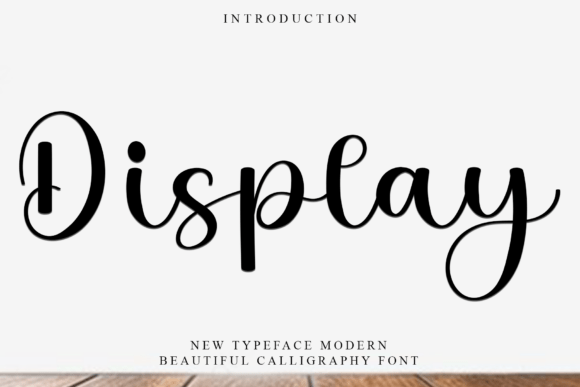
Display
Display – A Fonte Calligráfica que Transforma Seu Projeto
Se você busca uma tipografia que una elegância e versatilidade, a Display é a escolha ideal. Desenvolvida como uma fonte moderna de caligrafia, ela combina curvas suaves com traços marcantes, criando um visual refinado e ao mesmo tempo acessível. Perfeita para wedding invitations, cartões de felicitação, branding, logotipos, embalagens e design editorial, a Display garante que cada palavra pareça única e memorável.
- Ascendentes e descendentes fluídos: proporcionam um movimento gracioso que confere dinamismo ao texto.
- Contraste equilibrado entre linhas grossas e finas: aumenta a legibilidade sem perder a sofisticação.
- Charme de escrita à mão: traz um toque humano e acolhedor, ideal para projetos que precisam de personalidade.
- PUA encoded: acesso fácil a todos os glifos e ligaturas avançadas, facilitando a criação de layouts ricos.
- Versatilidade tipográfica: funciona impecavelmente em headlines impactantes ou em textos corridos fluídos.
Por que escolher a Display?
A Display não é apenas mais uma fonte; ela oferece delicadeza e confiança em cada caractere. Seu estilo atemporal eleva a comunicação visual, tornando‑a ideal para:
- Convites de casamento que precisam de um toque romântico.
- Cartões de felicitação que buscam transmitir carinho.
- Identidade visual de marcas que desejam destacar-se com personalidade.
- Embalagens premium que exigem sofisticação.
- Publicações editoriais que valorizam a leitura agradável.
Com sua combinação única de curvas elegantes e traços ousados, a Display se destaca como a solução tipográfica definitiva para designers que desejam imprimir beleza, personalidade e eternidade em cada projeto. Experimente a Display hoje e descubra como cada palavra pode ganhar vida própria.